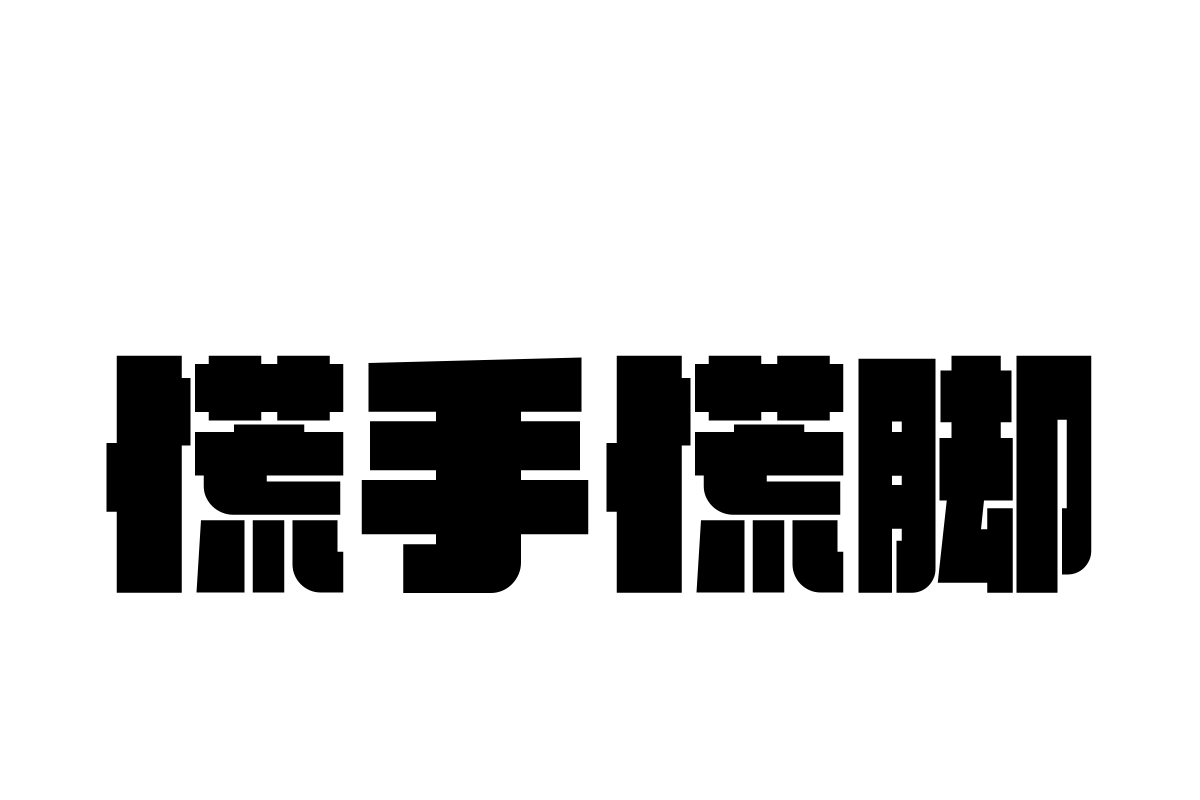
汉仪铸字班克斯繁体是一款由汉仪公司设计的中文字体。这款字体以其独特的设计和风格,深受设计师和用户的喜爱。以下是关于这款字体的一些介绍:
1. 设计风格:汉仪铸字班克斯繁体采用了一种简洁、现代的设计风格,线条流畅,字形规整。这种设计风格使得字体看起来更加美观大方,适合用于各种设计场景。
2. 字体结构:这款字体的结构紧凑,每个字符都经过精心设计,以确保整体的协调性和美感。这使得字体在视觉上呈现出一种平衡感,给人一种稳定而有力的感觉。
3. 字体特点:汉仪铸字班克斯繁体具有一些独特的特点,如笔画粗细的变化、字形的倾斜度等。这些特点使得字体在视觉上具有一定的辨识度,同时也增加了设计的趣味性。
4. 适用场景:这款字体适用于各种设计场景,如海报、广告、包装、书籍等。它不仅适用于商业设计,也适用于个人项目,如博客、社交媒体等。